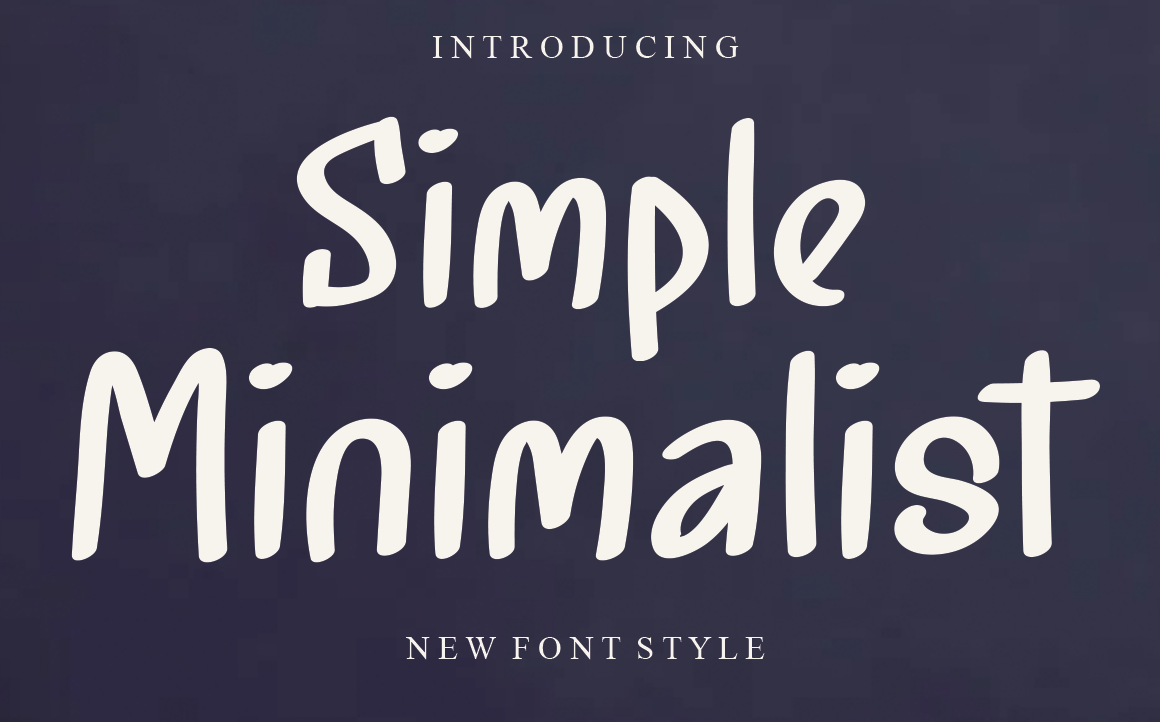
A fonte ‘Simple Minimalist Font’ é perfeita para quem busca uma mão escrita única que transmite leveza e simplicidade. Seja você criando conteúdo para a sua página do Instagram ou buscando um desenho de caligrafia para seus projetos DIY, esta fonte irá transformar suas ideias em verdadeiros trabalhos de arte. Com seu estilo minimalista e simples, ela é ideal para quem procura uma opção elegante e prática. Seja em postagens quebradas ou design de logotipos, este tipo pode ajudar a destacar sua mensagem com clareza e simplicidade. Especificamente projetada para designers que buscam um estilo descomplicado mas moderno, esta fonte não apenas reforça a natureza prática do seu trabalho, mas também oferece uma dimensão visual única, tornando-a perfeita para quem quer adicionar sua própria identidade à arte digital.